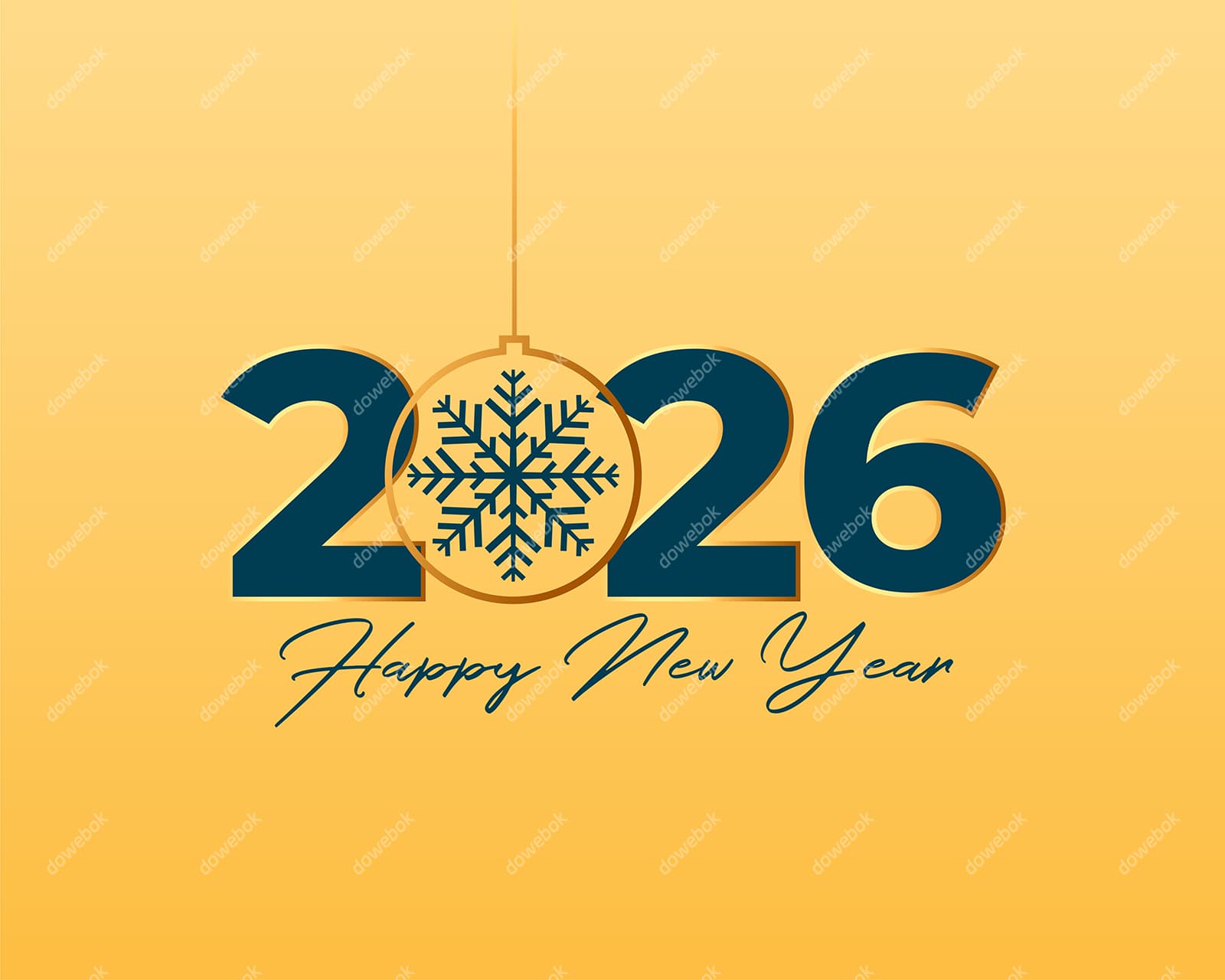
这是一款雪花吊坠和深蓝数字设计 2026 新年快乐矢量素材,暖黄渐变背景柔和温馨,深蓝 “2026” 字体边缘镶金,数字 “0” 化作带雪花纹的装饰球,似悬挂的节日挂饰。下方衬着优雅的花体 “Happy New Year”,整体以暖色调 + 冬日元素,既显跨年的温馨氛围,又用精致的装饰细节透出雅致的节日质感,柔和又亮眼。